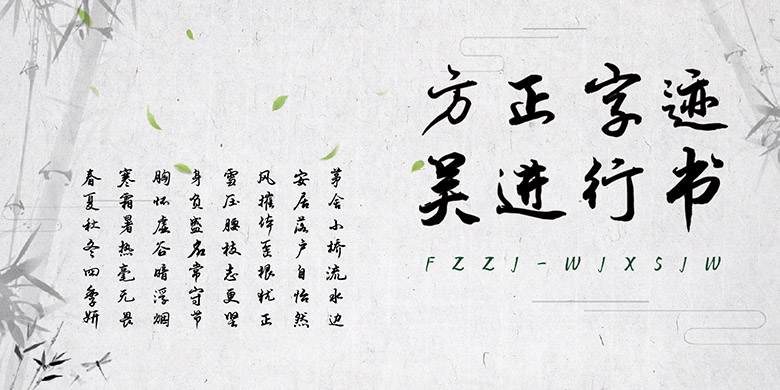
方正字迹-吴进行书
字体品牌: 方正字迹 设计师:吴进 字体分类:常规书写·毛笔 字体属性:精品字 字符集:大陆简体(GB2312-80)、简繁扩展(GBK) 发布时间: 2018
方正字迹-吴进行书是作者吴进长期研练的结果。该行楷提倡字形秀美,字体飘逸,笔力浑厚舒展,将魏体溶进笔意中,力求一笔完成,有机地将意和形达到平衡。